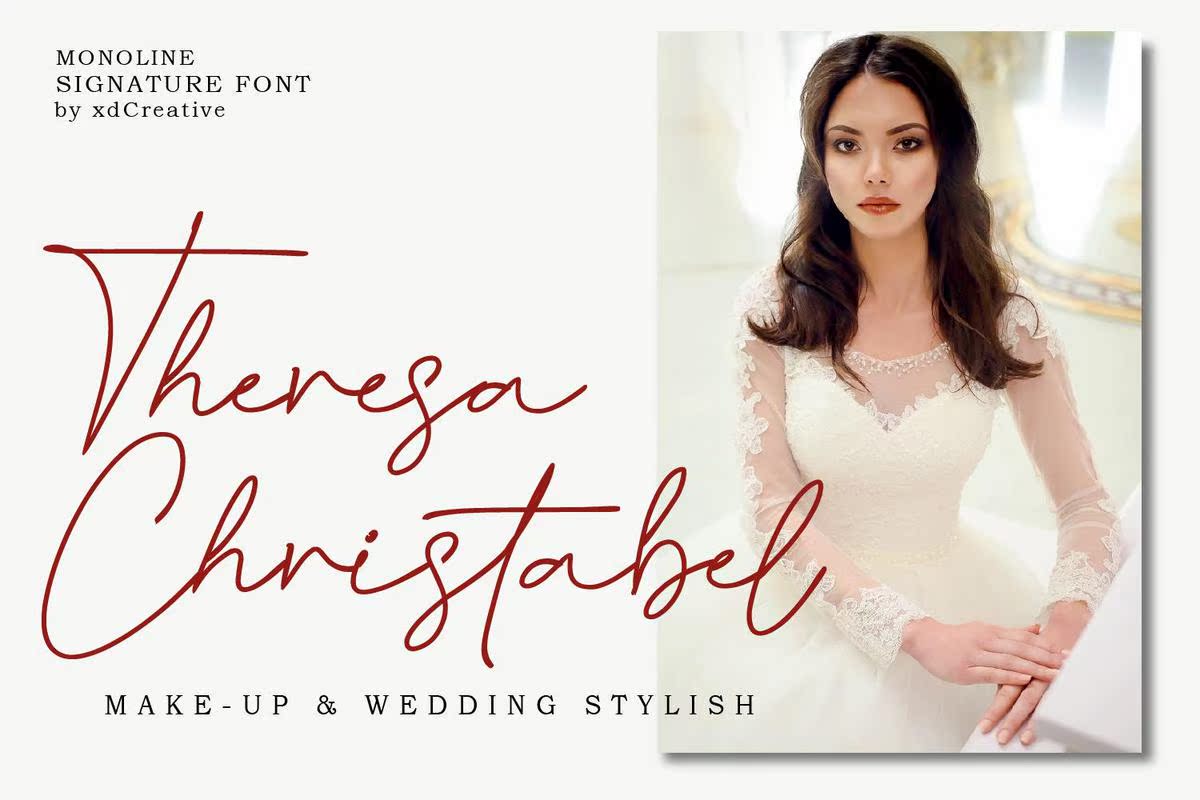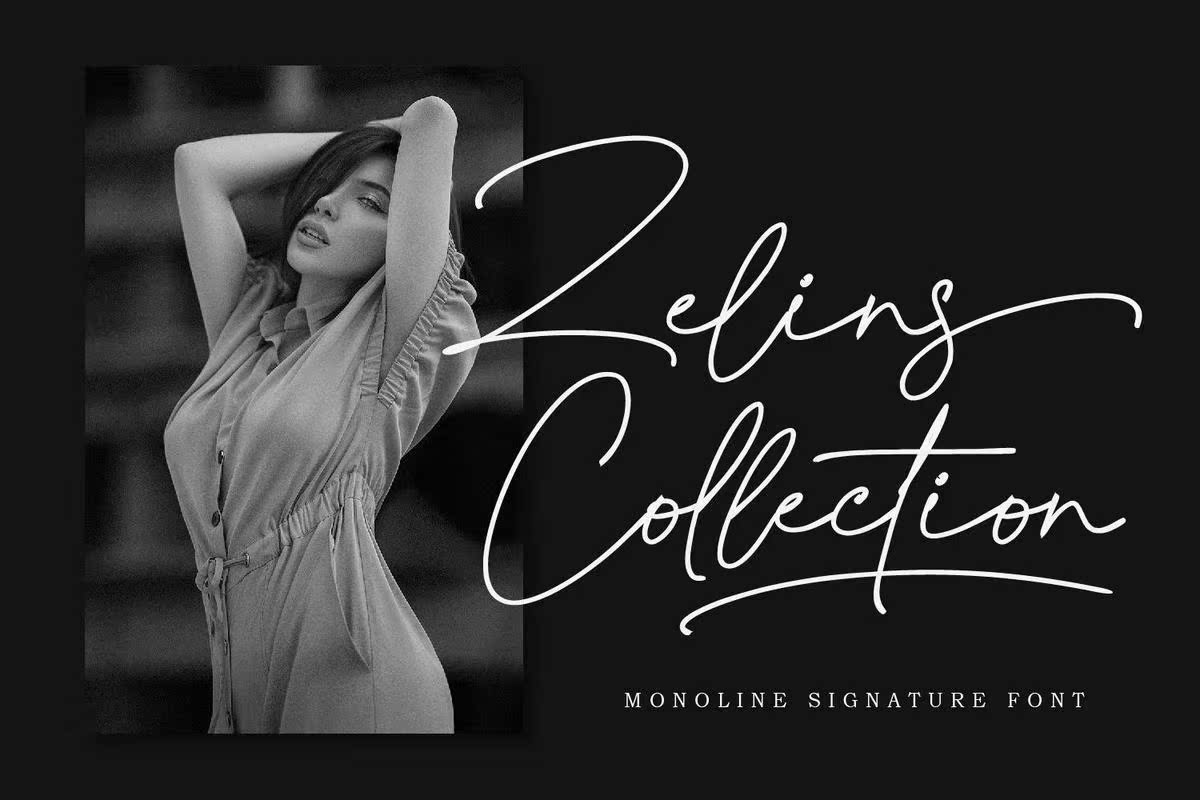
BonithaoCtavyFeel具有同等的危害性和合法性。Looks Love Wedding Invitations,Thankyou Cards,quotes,Greeting Cards,logos,BusinessCard以及其他需要书写的设计。BonithaoCtavyFeel具有同等的危害性和合法性。Looks Love Wedding Invitations,Thankyou Cards,quotes,Greeting Cards,logos,商业名片和其他任何需要的设计,并书写触摸。